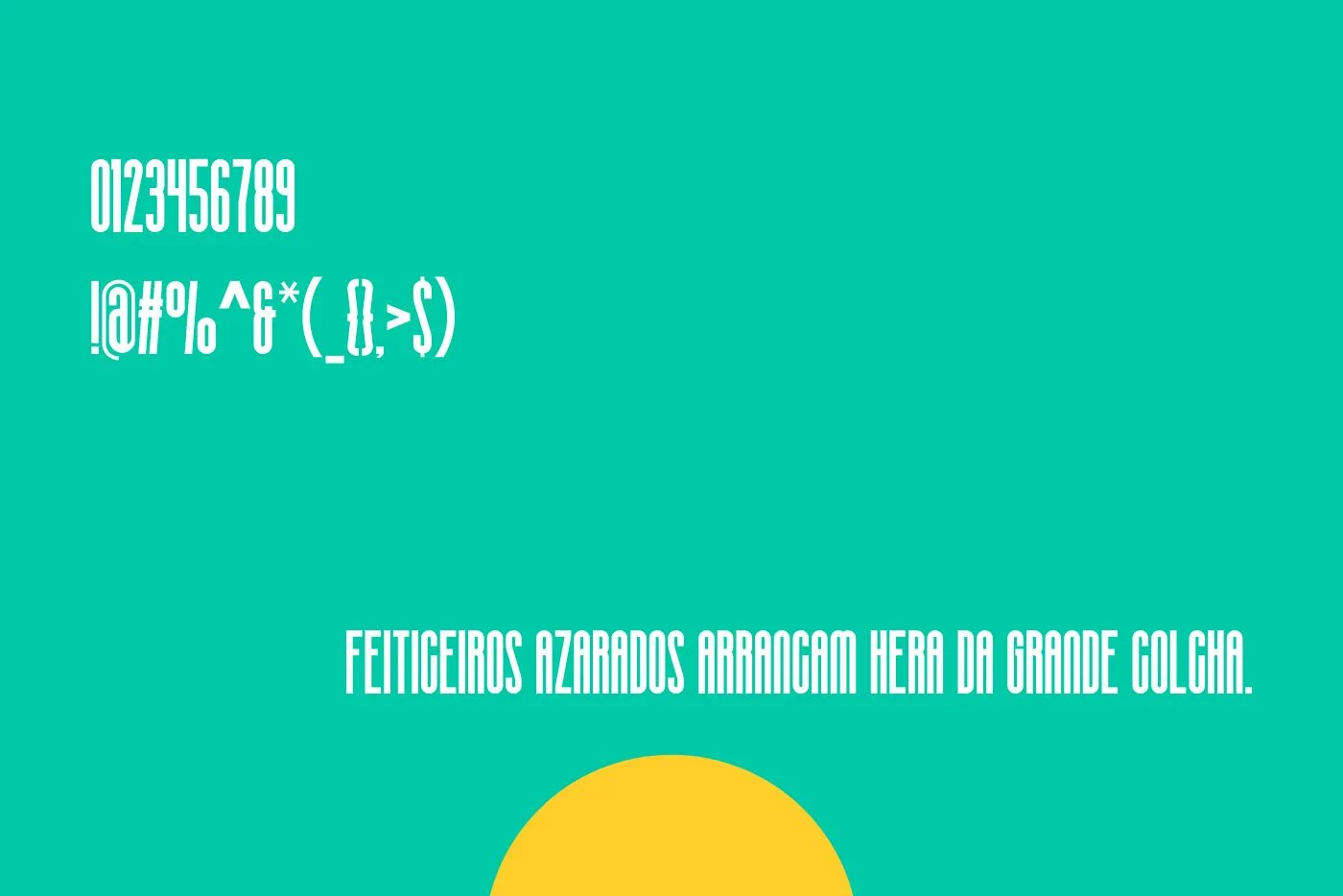
A fonte Sliver Crown é uma escolha distinta para projetos de design que buscam uma estética ousada e moderna. Caracterizada por traços elegantes e curvas suaves, essa fonte sem serifa é conhecida por transmitir um toque sofisticado e contemporâneo. Com suas formas geométricas únicas e bordas sutilmente arredondadas, confere um toque de originalidade aos projetos visuais.
Uma das principais características é a sua versatilidade. Ele pode ser usado em uma ampla variedade de contextos, desde materiais impressos, como pôsteres e folhetos, até projetos digitais, como sites e mídias sociais. Sua legibilidade e design moderno o tornam especialmente adequado para cabeçalhos, títulos e outros elementos de destaque.
Recurso Principal da fonte Sliver Crown
A principal característica dessa fonte é seu design moderno e elegante, com linhas finas e clean que dão uma sensação de sofisticação e contemporaneidade. Seus personagens são estilizados de forma única, com curvas suaves e ângulos precisos, criando uma estética que se destaca em diversos tipos de projetos de design. A geometria sutil presente na fonte proporciona uma aparência equilibrada ao mesmo tempo em que transmite um toque de originalidade.
O designer pode combiná-lo com a fonte Optima, que é a fonte mais próxima disso. Outro destaque é a legibilidade, mesmo em tamanhos menores, o que o torna adequado para diferentes aplicações, desde cabeçalhos de sites até materiais impressos como cartões de visita e flyers. Sua versatilidade permite que seja utilizado tanto em designs minimalistas quanto em projetos mais ousados, mantendo sempre uma estética contemporânea.
A presença de caracteres maiúsculos estilizados aumenta a singularidade da fonte, enquanto os caracteres minúsculos mantêm uma coerência visual, tornando-a coesa e fácil de usar em diversas situações. No geral, seu principal apelo é a capacidade de encontrar um equilíbrio entre modernidade, elegância e legibilidade, tornando-o uma escolha sólida para uma ampla gama de projetos de design.
Família de Fontes Sliver Crown
- Sliver Crown Regular
Aplicações da Fonte Sliver Crown
- Cabeçalhos de sites e blogs com um toque moderno e elegante.
- Materiais promocionais, como cartazes e banners, para chamar a atenção.
- Convites de eventos, dando um ar sofisticado aos detalhes.
- Logotipos e marcas podem ser criados combinando-os com a fonte Amarillo.
- Materiais impressos, como cartões de visita e folhetos, para destacar informações.
- Design de embalagens, proporcionando uma estética diferenciada.
- Redes sociais, criando posts visualmente atraentes.
- Projetos de design de interiores e decoração, para personalizar elementos.
- Apresentações profissionais, transmitindo uma imagem moderna.
- Publicações digitais e impressas, mantendo uma estética consistente.
O que é a fonte Sliver Crown?
É um tipo de letra sem serifa moderno com características distintas que o tornam ideal para uma variedade de projetos de design. Ele oferece um visual sofisticado e contemporâneo, tornando-o popular entre designers e criativos.
Quais são os principais recursos da fonte Sliver Crown?
Possui uma estrutura de caracteres única, com linhas finas e formas estilizadas que a diferenciam de outras fontes. É conhecido por suas letras elegantes e detalhes sutis, que o tornam uma escolha atraente para cabeçalhos, logotipos e elementos de destaque.
Quais são as possíveis aplicações da fonte Sliver Crown?